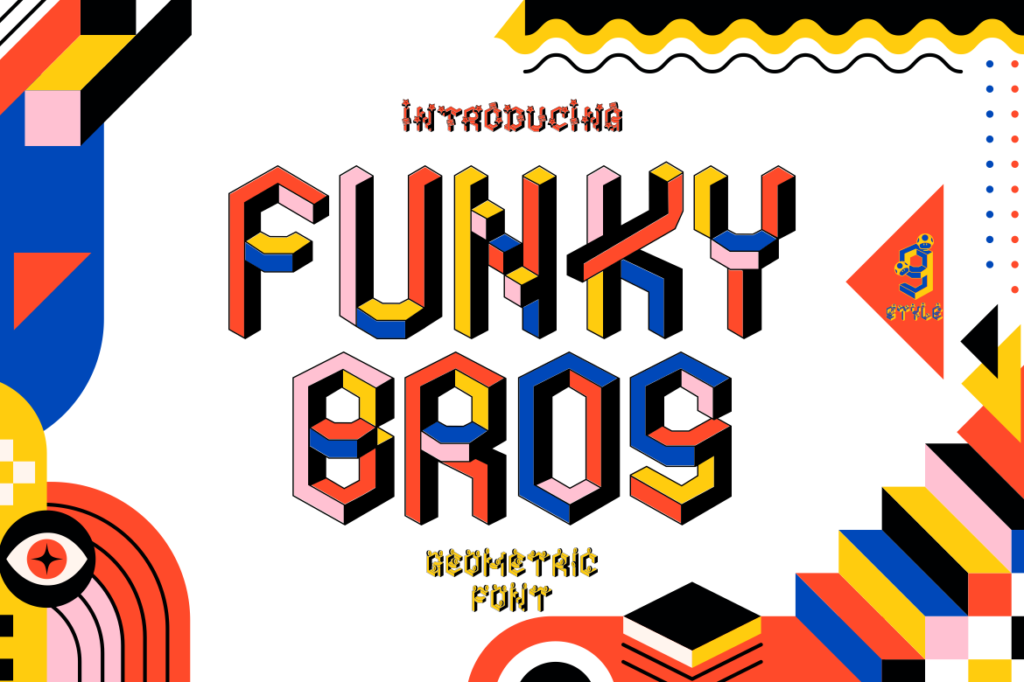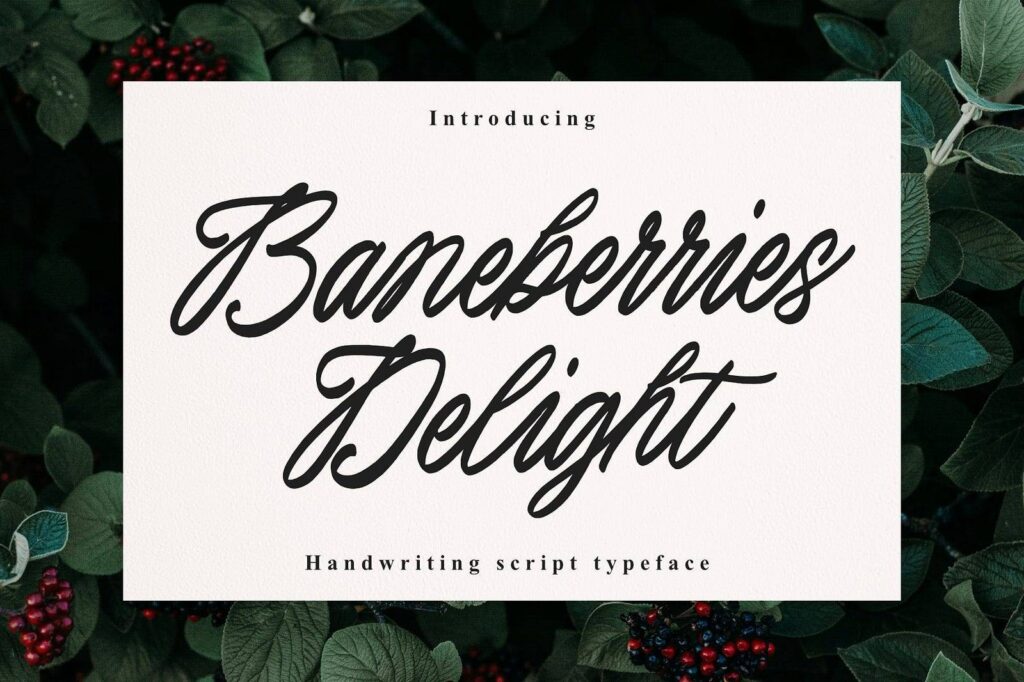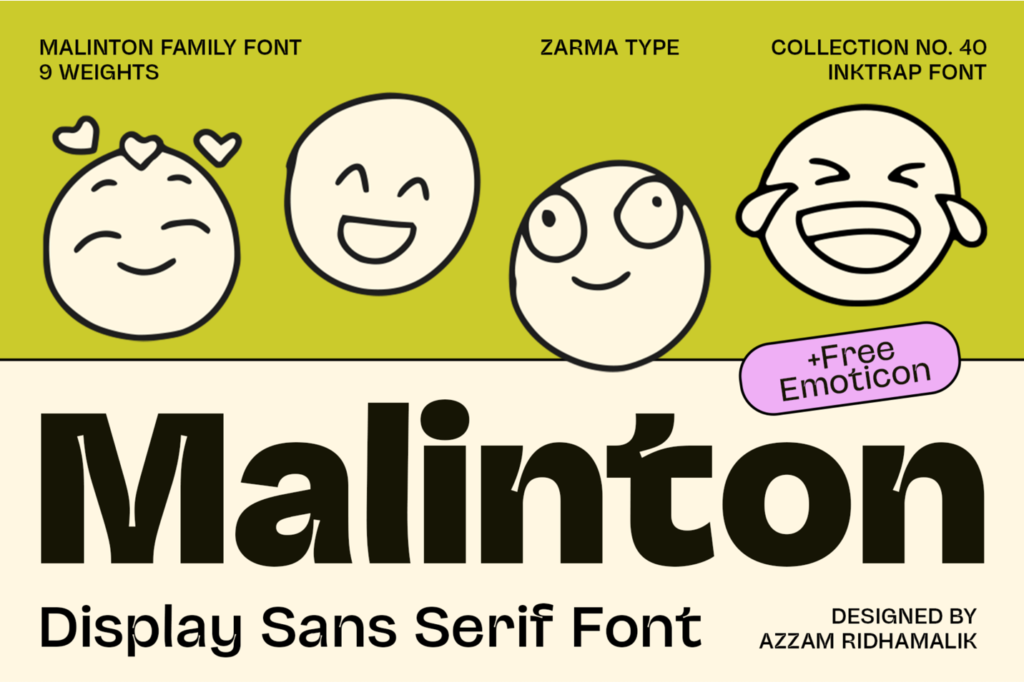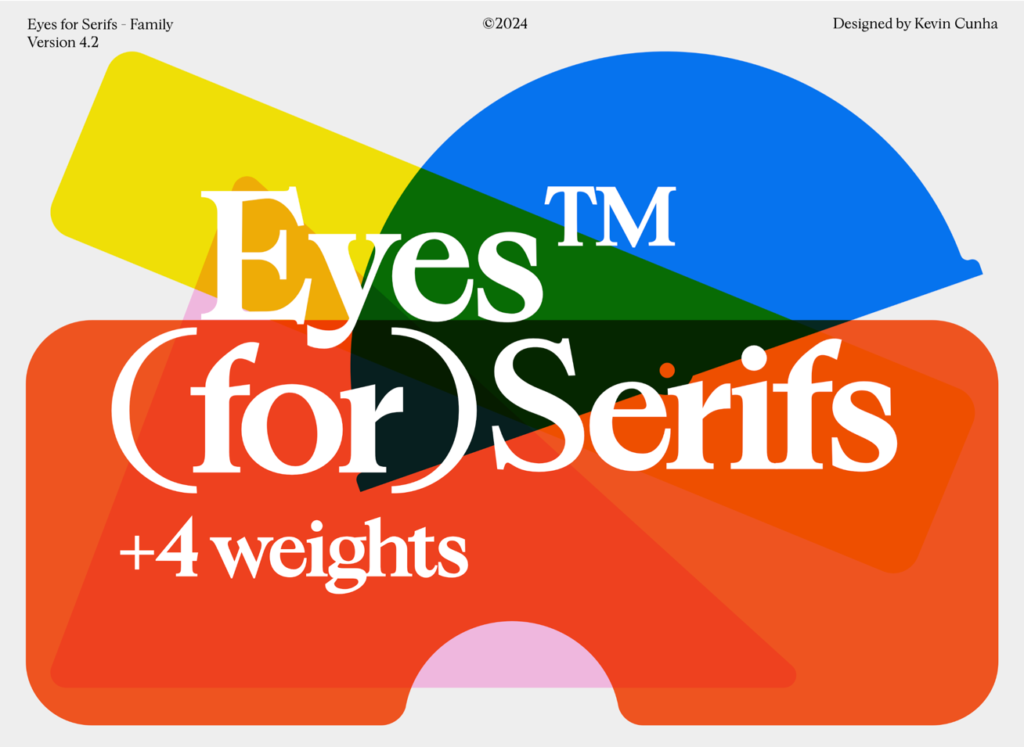
30种优秀免费时尚设计字体
30种优秀免费时尚字体
选择合适的字体可以大大提升项目的视觉效果。在 2025 年到来之际,我们非常高兴地向您推荐 30 种优秀的免费字体,它们将为您的设计带来风格和个性。
1. Mansfield Font
Mansfield 字体是一个清新、多功能的几何无衬线字体系列,其灵感来源于 20 世纪的标志性字体,如 Futura 和 Avant Garde。Mansfield 字体采用几何字形,边缘锋利,笔画对比度极小,体现了新古典主义字体简洁、现代的美感。其较高的 x 高度和精确的设计使其成为各种设计项目(从品牌设计到编辑工作)的完美选择。
2. Neue Power
Neue Power 是一个现代无衬线显示字体系列,有 6 种大小和 12 度斜体。它支持 75 种以上的语言(基于拉丁语),其次是 Grotesk 字体,非常适合各种设计需求。
3. Madeleine Stories
Madeleine Stories 字体是一种制作精美的手写脚本字体,体现了优雅、温暖和多功能性。凭借流畅的手写笔画和精致的细节,这款字体给人既个性又精致的感觉,非常适合各种创意项目。
4. Eyes for Serifs
Eyes for Serifs 这款字体总结了经典人文字体的范例,但加入了个性化细节,更加俏皮可爱。它的目标是使字体具有更强的可读性,专注于编辑和印刷用途,但又不失趣味性。
5. Regar Font
Regar 是一款现代而醒目的显示字体,专为大胆的声明和视觉冲击而设计。其简洁的线条、独特的字形和时尚的美感使其成为标题、海报、品牌和编辑设计的完美选择。Regar 字体兼顾了优雅和可读性,在保持清晰度的同时又显得与众不同,因此既适用于印刷品,也适用于数码产品。对于需要强烈现代气息的项目来说,Regar 是理想之选,它能吸引注意力,给人留下难忘的印象。
6. Nostalgic Remain Font Family
Nostalgic Remain 是一种别致的现代永恒衬线字体,唤起人们的怀旧感和旧世界的魅力。其优雅而精致的字形非常适合创作需要精致和传统气息的设计。
7. Better minds Font
Better minds 由时尚的手写体组成,看起来优雅而时尚。该字体包含 15 个连字符,看起来尽可能接近自然的手写体。
8. LT Serif
LT Serif 是一款现代、简约、优雅的衬线字体,其特点是可选择带柄的大写字母。这款多功能字体包含大写字母、小写字母、符号、备用字母、数字,并支持多语言字符。LT Serif 非常适合要求精致和现代风格的项目,如杂志标题、书籍版面、横幅、海报、徽标等。
9. Galter Font
Galter Font 该字体的特点是笔画粗细比例均衡,可创造出极具吸引力且易于阅读的视觉效果。这种现代衬线字体的特点通常是粗细线条之间的大胆区分,给人一种低调而又突出的感觉。
10. Rightes South Font
Rightes South Font 是一款时尚的手写字体,集优雅与现代感于一身。这款字体拥有流畅的曲线和活泼的形状,非常适合突出美感和个性的设计。其独特的笔画赋予了它别致、现代的外观,使其成为许多设计项目的最佳选择,无论是引人注目的徽标、浪漫的婚礼请柬,还是高级、精致的品牌形象,都可以使用它。
11. Funky Form
一种前卫的字体,旨在为您的创意项目带来新意。这款字体独特地融合了显示风格和几何风格,以其等距风格和块状字符脱颖而出,在保持专业完整性的同时,还唤起了一种俏皮感。Funky Form – Geometric Font 非常适合以游戏为主题的设计或任何需要引人注目的项目,在提供多功能性的同时又不失风格。
12. Longblack
向 Longblack 字体问好!这款优雅的字体毫不费力地将时尚与精致融为一体,是您所有创意项目的不二之选。无论您是设计徽标、邀请函还是社交媒体文章,Longblack 字体都能带来平滑的平衡,给人留下深刻的印象。
13. SK Concretica
SK Concretica 这款字体的灵感来自 Adrian Frutiger、Eric Spickerman、Claude Garamon 等字体设计大师的作品。字体渗透着现代主义和纪念碑式的精神。这款字体拥有平面设计师所需的一切:基本字符集(拉丁文和西里尔文)、附加多语言字符集(希腊文、希伯来文、平假名、片假名)、扩展基本字符集(拉丁文专业版、西里尔文专业版)、字母和标志的替代样式、箭头(基本和替代集)等等。
14. Rany Typeface
这款名为 “Rany” 的字体是一款现代几何无衬线字体,设计简洁,用途广泛。Rany “是由一位设计师将自己的想法变为现实而创作的,非常适合徽标、标题、网页和移动 UI 设计。尽管创作者并不是专业的字体设计师,但他们的目标是设计出一种易于使用、功能强大、适用于各种应用的字体。
15. Neopixel
一款散发着未来主义和现代风格的显示字体。每个字符都体现了创新精神,在任何设计中都能产生强烈的冲击力。使用精致的 Neopixel 字体增强您的视觉项目–在这里,进步与鼓舞人心的字体设计相遇。
16. Baneberries Delight Font
Baneberries Delight 是一款迷人的手写体字体,集优雅与奇思妙想于一身。这款字体拥有流畅的手绘笔触和精致的曲线,捕捉到了手写书法的自然优雅和魅力,为任何设计都带来了温馨感和个人风格。
17. Malinton
Malinton 是一款俏皮多变的无衬线显示字体,旨在以个性和风格提升您的设计。它有 9 种重量、360 多个字形,支持 85 种以上的语言,还有独特的表情符号,非常适合用于徽标、社交媒体、标题等。通过现代墨迹和可变字体技术,Malinton 在创意和专业性之间取得了理想的平衡。
18. Englisch Type Family
Englisch 是一款显示字体,灵感来自 17 和 18 世纪的英国字体设计,融合了传统影响和现代元素。该字体有 6 种重量和 12 种样式,具有垂直对比、开放形式和俏皮的设计细节等特点,是大胆的标题和徽标的理想选择。适用于印刷和网络,支持扩展拉丁字母。